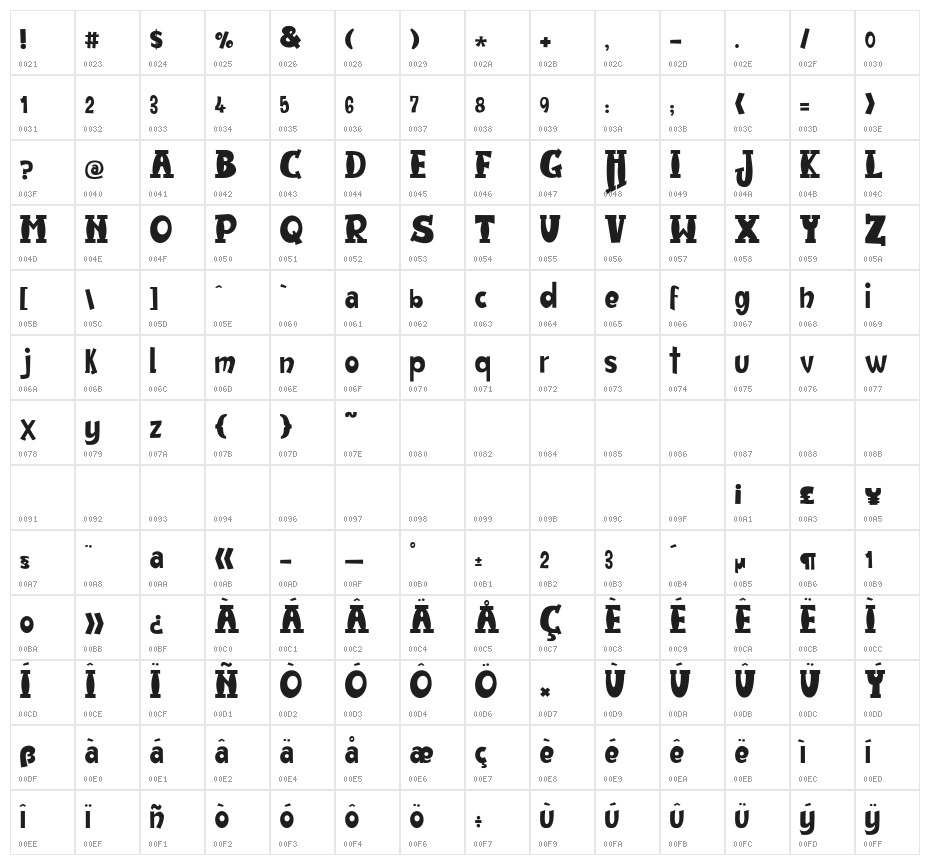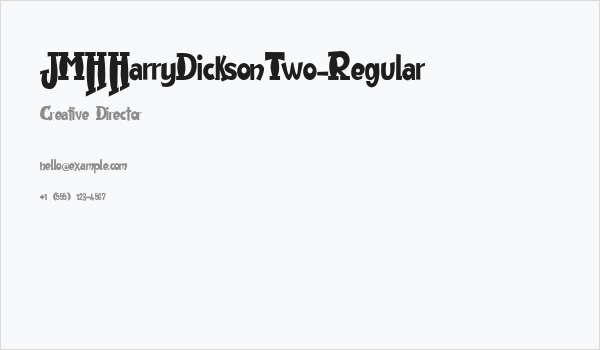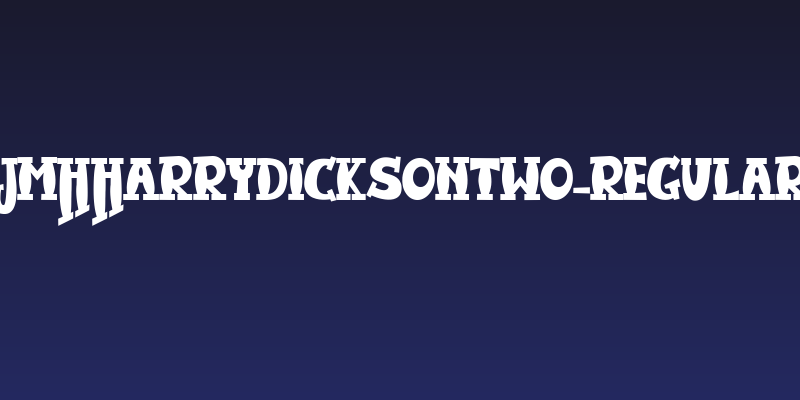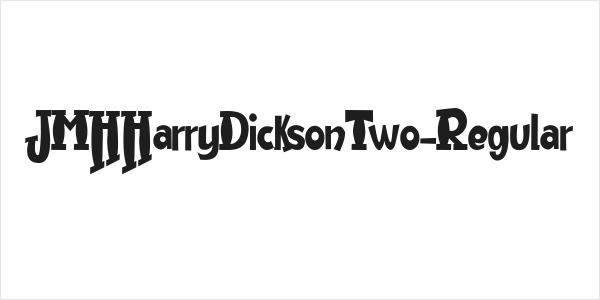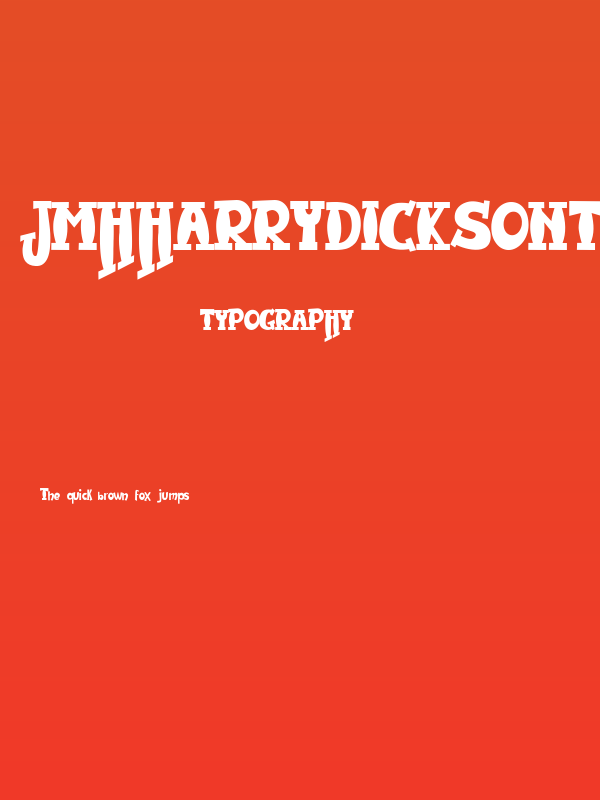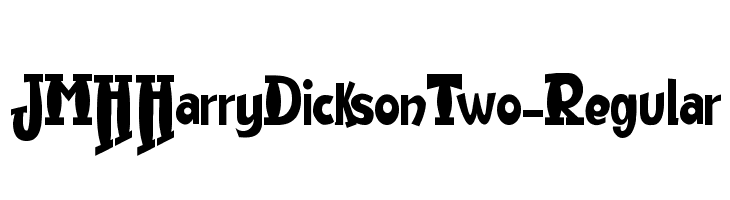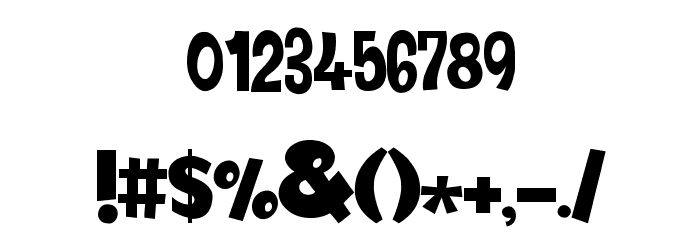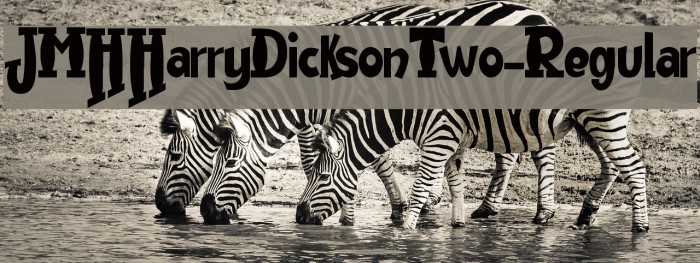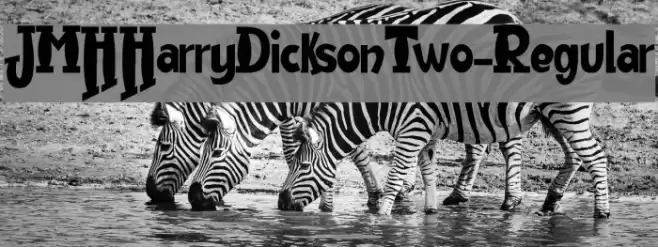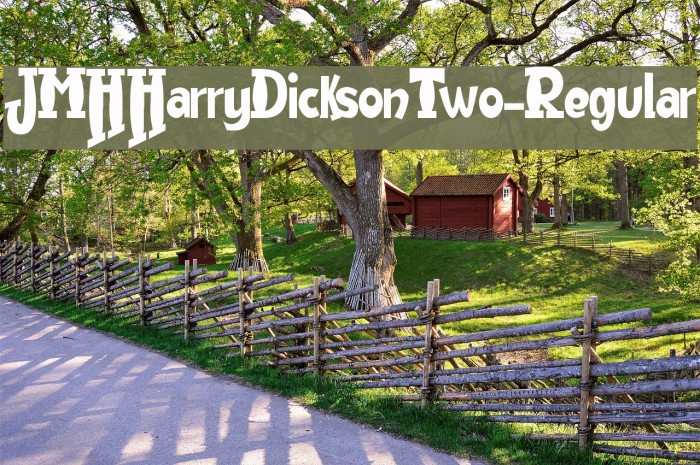
JMHHarryDicksonTwo-Regular Font
| Gesamtstil | Vintage |
| Vorgeschlagene Projekte | Ideal for retro-themed posters, playful branding, children's book covers, and eye-catching headlines. |